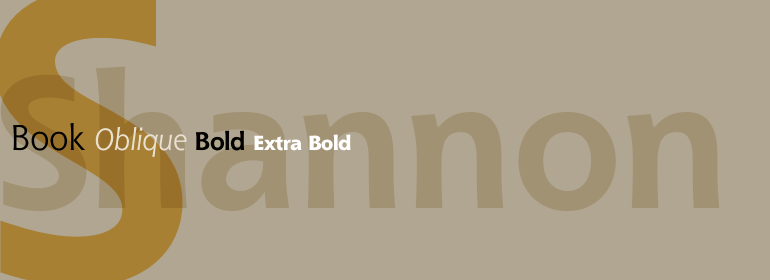
Shannon™
清晰易读的Shannon字体家族是由Janice Prescott Fishman和Kris Holmes在1982年专为Compugraphic设计的。它的设计融合了来自《Book of Kells》的古代爱尔兰的书法和现代字母的形式。Shannon是一种改进的无衬线字体,带有略微张开的末端,可产生衬线效果,从而有助于提高可读性。Shannon的理想用途非常广泛:从广告和杂志到幻灯片和数据表。
The highly legible Shannon font family was designed by Janice Prescott Fishman and Kris Holmes exclusively for Compugraphic in 1982. Its design blends ancient Irish calligraphy from the Book of Kells and contemporary letterforms. Shannon is a modified sans serif typeface with slightly flared terminals that give the effect of serifs, thus aiding readability. Shannon is ideal for a whole range of uses: advertising and magazines to slides and data sheets.